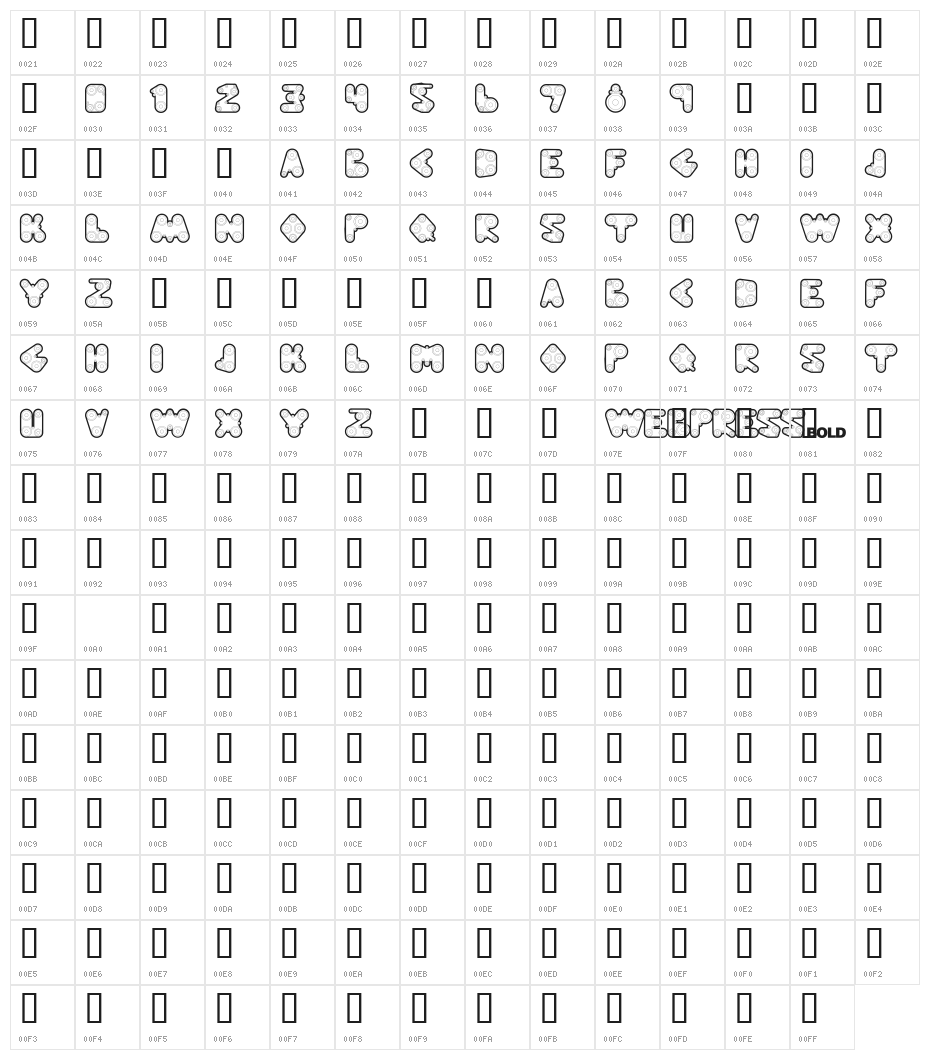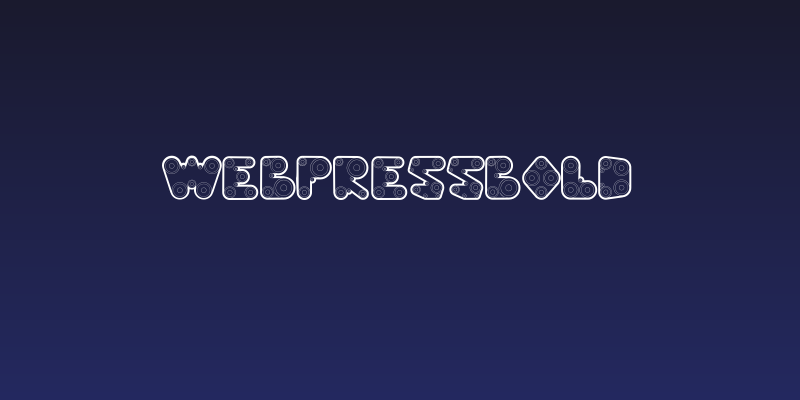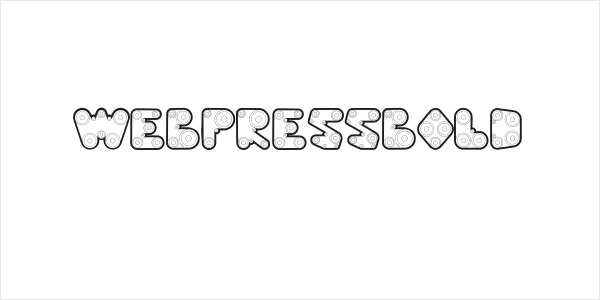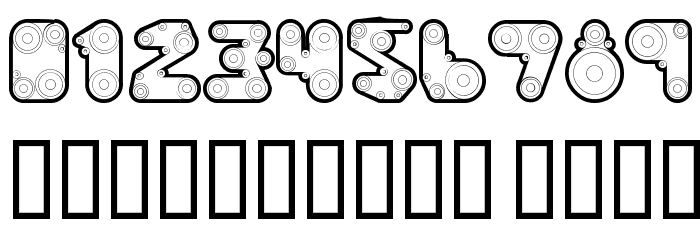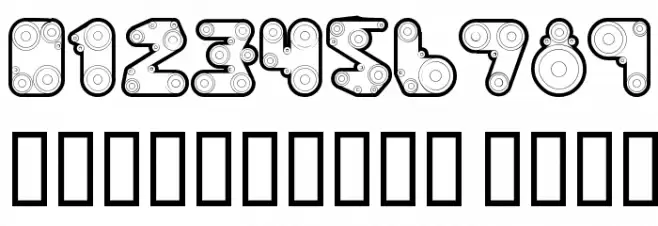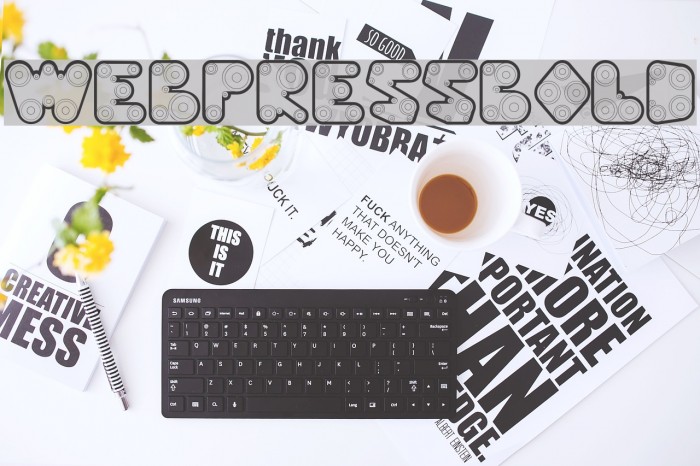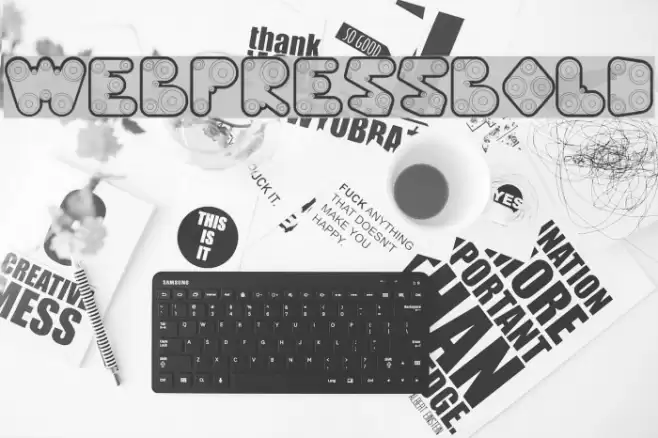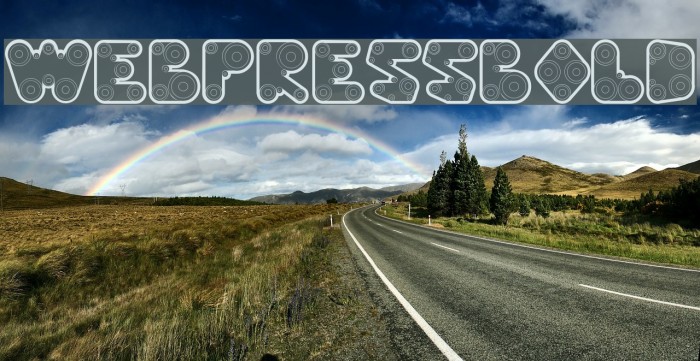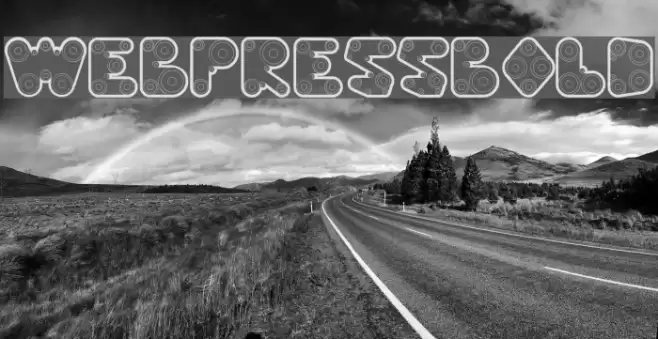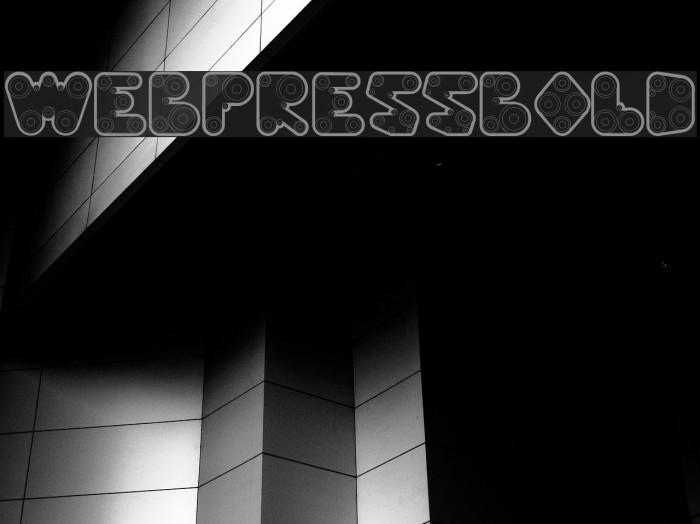
WebPressBold Font
| Anwendungsfall | Logos, Posters, Branding |
| Vorgeschlagene Projekte | Ideal for posters, logos, and branding materials that require a bold, industrial aesthetic. |